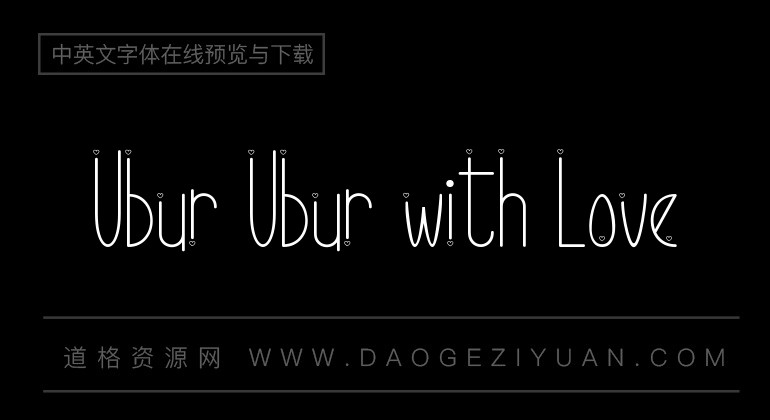
Ubur Ubur with Love
Ubur Ubur with Love 是一款免费的手写风格字体,由印度尼西亚的设计师Agga Swist'blnk制作。该字体的设计灵感来自于印度尼西亚的传统文化和手写草书等元素,因此具有浓厚的艺术气息。 Ubur Ubur with Love 字体包含大小写字母、数字、标点符号和一些特殊字符,非常适合用于海报、卡片、标志和其他艺术设计项目。此外,该字体非常易于阅读,可以在不同的尺寸和背景下使用。总的来说,Ubur Ubur with Love 是一款非常有趣和多用途的字体,为各种项目带来了独特的风格和魅力。
Ubur Ubur with Love是一款非常不错的手写艺术字体,具有很好的视觉感,适合于文化类的宣传设计、商业类品牌的广告和产品包装设计以及个性化文字排版等较多场景。